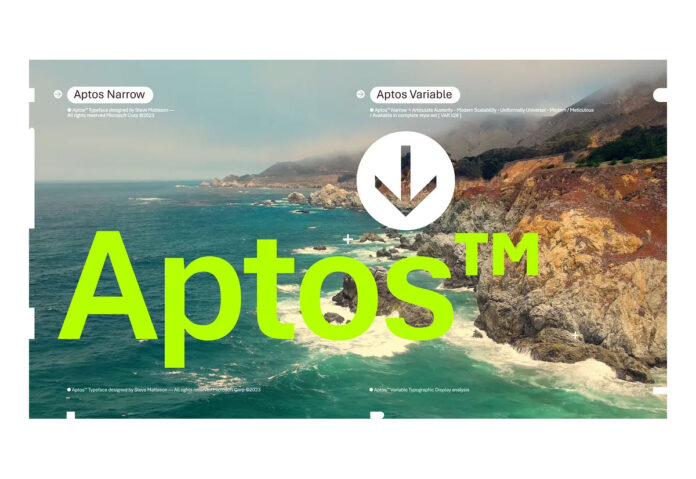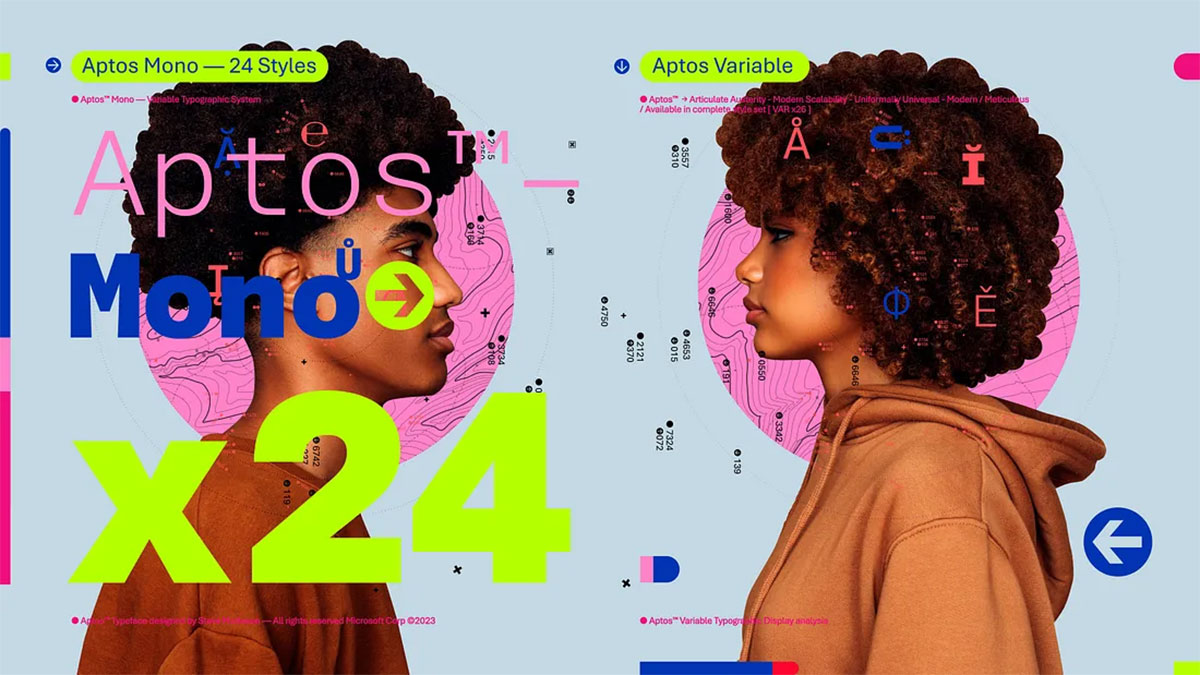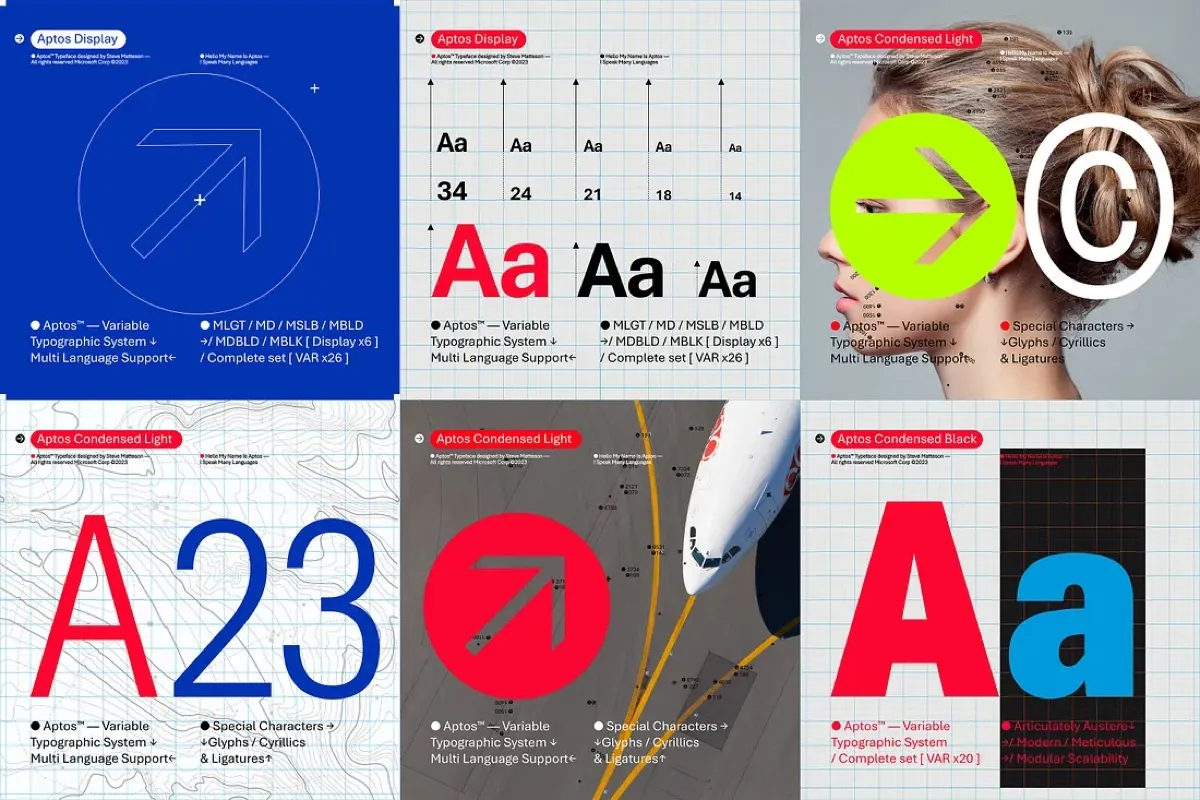
Microsoft Office cambia font dopo 15 anni, ecco Aptos
Microsoft ha deciso di sostituire Calibri – il font di default proposto dal 2007 in Word, Excel, PowerPoint e altre app di Office – con un carattere denominato Aptos, un font san serif (senza grazie) ispirato “alla tipografia svizzera della metà del XX secolo”.
In precedenza noto come Bierstadt, in un comunicato stampa Microsoft riferisce che il carattere in questione “inizierà ad apparire come nuovo font predefinito in Word, Outlook, PowerPoint ed Excel per centinaia di milioni di utenti” e che “nei prossimi mesi diventerà l’impostazione di default per tutti i nostri clienti”.
Aptos è stato creato da Steve Matteson, responsabile type design di Microsoft, la stessa persona che in precedenza ha creato Segoe, concesso in licenza a Microsoft come font di default in Windows. Microsoft – riferisce The Verge – ha cominciato a usare la sottofamiglia di font Segoe UI in Windows Vista e ancora oggi questo carattere è usato in Windows 11.
Microsoft Office cambia font dopo 15 anni: arriva Aptos
Matteson ha lavorato anche allo sviluppo dei font TrueType inclusi nelle prime versioni di Windows. In un post su Medium, Matterson riferisce di avere creato il nuovo carattere “con un leggero tocco umanista”. E ancora: “Volevo che Aptos avesse il fascino universale del defunto giornalista della NPR Carl Kasell e il tono astuto del conduttore di The Late Show Stephen Colbert”.
Aptos è un carattere senza grazie con tratti facilmente leggibili. “Le estremità dello stelo sono pulite. Sottili quadrati circolari all’interno dei contorni delle lettere consentono una maggiore leggibilità, soprattutto a piccole dimensioni”. Ricordiamo che il processo di selezione del nuovo font è iniziato nel 2021: Microsoft aveva presentato cinque candidati potenziali tra i quali poi utenti e clienti hanno scelto Aptos.Microsoft Office cambia font dopo 15 anni, ecco Aptos